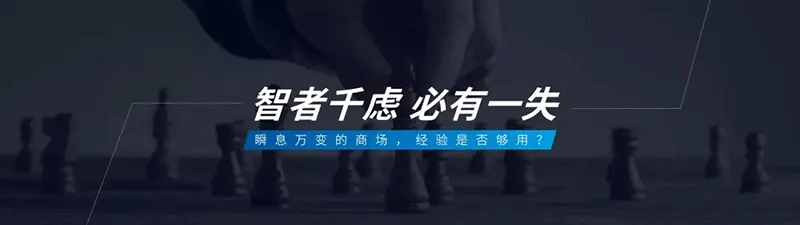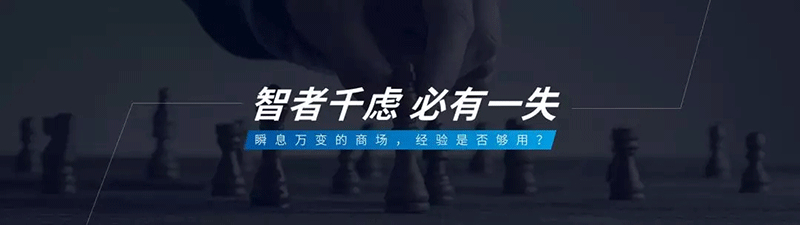
演示斜黑體是Keynonte研究所基於思源黑體改造而來的傾斜體字體,優秀的字體往往可以透過字形與筆畫風格的設定將其蘊含的情感傳達給受眾,甚至要優於人們理解這些文字的句意之前。身處於互聯網時代,無襯線字體以其“中庸”的姿態崛起於移動端設備。傾斜字體往往能為畫面營造出極強的速度感。
傾斜字體往往能為畫面營造出極強的速度感,演示斜黑體定位於標題。